Ternyata Nggak Ribet, Begini Cara Mengubah Font di Instagram. Pernah bosen nggak sih dengan font yang itu-itu saja di Instagram? Tentu pernah dong ya.. memang, font atau gaya tulisan merupakan salah satu daya tarik yang bisa memikat pengguna untuk menggunakan suatu aplikasi. Meskipun jarang diperhatikan, penggunaan font yang beraneka macam akan membuat para pengguna menjadi tidak jenuh dalam bermain aplikasi.
Nah, bagi kamu pengguna setia Instagram dan jenuh dengan font yang itu-itu saja, bisa banget nih kamu coba untuk mengubahnya melalui cara dibawah ini, kamu penasaran? Yuk simak 22 Cara Ubah Font Instagram Agar Tidak Membosankan dibawah ini.
22 Cara Ubah Font Instagram Agar Tidak Membosankan Sbb:
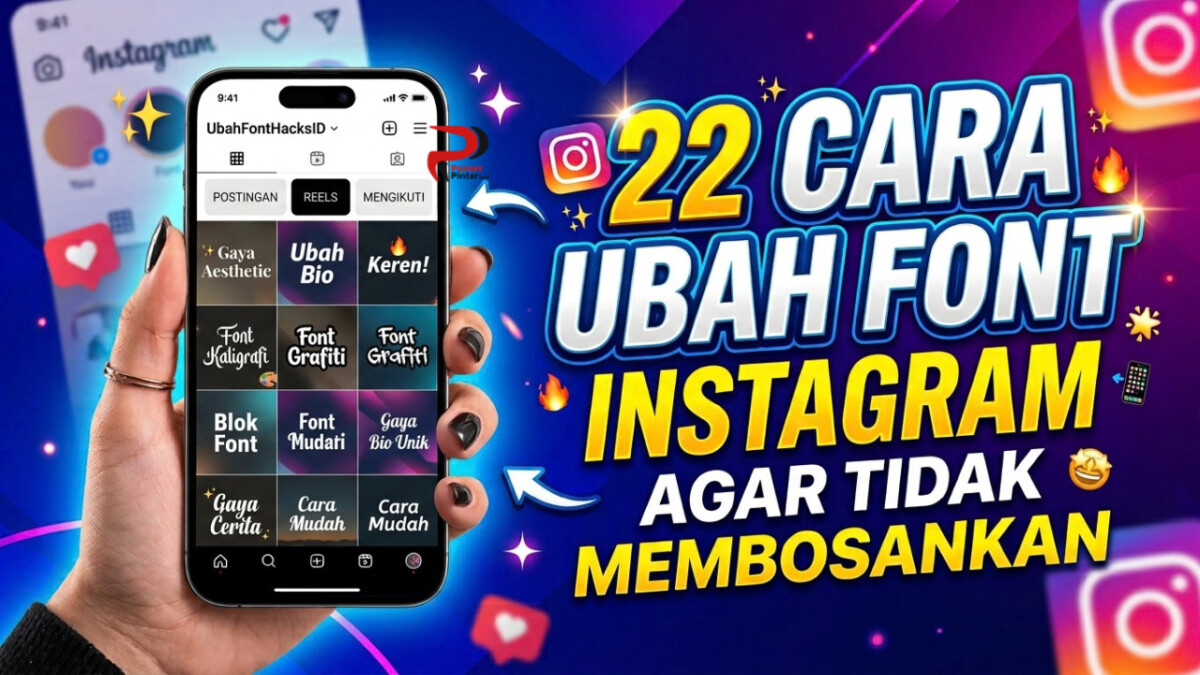
Dengan penggunaan font yang unik dan beda dari yang lain, bio Instagrammu akan tampak lebih menarik dan pastinya estetik. Untuk mengubah font Instagram menjadi lebih menarik, berikut cara-cara yang bisa kamu lakukan:
1. Generator Font Sosmed
Mengubah font sosial media, termasuk Instagram menjadi lebih unik dan estetik sangat mudah untuk dilakukan. Karena saat ini, sudah banyak generator online yang memang menyediakan layanan pengubah font ini. Bahkan untuk menggunakannya pun sangat mudah tanpa perlu login atau mendaftar akun.
Salah satu generator online yang bisa Anda manfaatkan untuk mengubah font Instagram menjadi lebih unik adalah Generator Font Semua Sosmed yang tersedia pada situs Convertmee.com. Bukan hanya Instagram saja, namun generator ini kompatibel dengan sosmed lainnya seperti WhatsApp, Facebook, TikTok, dan sebagainya.
Pada generator tersebut, Anda akan menemukan sejumlah gaya teks estetik dan unk yang bisa dipilih untuk mengubah teks standar dan digunakan di Instagram. Adapun langkah-langkah penggunaannya adalah sebagai berikut:
Apabila ingin melihat jenis teks unik dan estetik lainnya yang tidak ada di generator ini, Anda bisa mengakses generator lainnya yang juga tersedia di situs Covertmee dan mendukung penggunaan di Instagram pula. Misalnya seperti Fancy Text Generator, Generator Font Instagram, Generator Font Simbolik, dan sebagainya.
2. Cool Symbol
Situs ini juga menyediakan berbagai koleksi jenis teks unik yang dapat Anda gunakan untuk mengubah teks standar.
3. LingoJam
LingoJam pun dapat Anda kunjungi untuk menemukan berbagai jenis teks unik lainnya.
4. Meta Tags Font Generator
Anda juga dapat melihat pratinjau saat mengubah font dengan layanan ini.
5. Instafonts
Berbagai jenis font dapat Anda temukan juga pada situs ini untuk digunakan di Instagram.
6. Font Bio
Platform ini dirancang secara khusus untuk membantu pengguna Instagram merapikan bio hingga caption postingan.
7. Cool Font
Variasi teks unik bisa Anda lihat dan gunakan juga pada situs Cool Font.
8. Fancy Text Guru
beraneka ragam huruf atau teks bergaya bisa didapatkan juga setelah mengunjungi platform ini.
9. Piliapp
Generator teks unik lain yang juga bisa dioertimbangkan untuk digunakan adalah Piliapp.
10. Font Changer
Mengubah huruf standar menggunakan Font Changer juga dapat dilakukan dengan mudah.
11. Fonts Online
Alternatif lain yang bisa Anda gunakan untuk menemukan font unik adalah Fonts Online.
12. Logwork Instagram Fonts
Jika ingin mengubah tulisan menjadi glitch, platform ini cocok untuk dicoba.
13. Fonts Studio
Beragam jensi tulisan unik bisa didapatkan melalui situs satu ini juga.
14. IFonts
Alat untuk mempercantik profil Instagram dengan tulisan unik juga dapat ditemukan pada situs IFonts.
15. Text Trick
Teks bergaya artistik bisa Anda bentuk di situs Text Trick.
16. Instagram Fonts FR
Merupakan salah satu situs web dengan bahasa prancis yang dapat membantu untuk urusan font estetik.
17. Bold Texts
Lebih berfokus pada teks tebal dan miring. Jadi jika Anda membutuhkannya, Anda juga dapat mengakses Bold Texts.
18. Aesthetic Font
gay huruf dan lembut bisa Anda gunakan pada Aesthetic Font.
19. Fancy Text Tool
Memodifikasi huruf standar bisa dilakukan juga dengan menggunakan Fancy Text Tool.
20. Unicode Text Converter
Huruf biasa bisa Anda ubah juga menjadi kode karakter khusus unicode unik dengan menggunakan Unicode Text Converter.
21. IGFonts
Cara pertama untuk dapat mengubah font Instagram adalah melalui IGFonts. Adapun langkah-langkah penggunaannya adalah sebagai berikut:
- Pertama, kunjungi situs igfonts.io terlebih dahulu
- Kemudian, silahkan Anda ketik teks yang akan Anda cantumkan pada profil IG di kolom “Add text here”
- Berikutnya, Anda dapat scroll ke bawah
- Lalu Anda dapat menemukan pilihan font yang muncul dalam beberapa saat. Terdapat beberapa pilihan font yang tersedia dan bisa Anda gunakan secara gratis
- Sedangkan pada bagian bawah, Anda dapat melihat hasil teks yang telah Anda ketik sebelumnya dengan pilihan font yang beragam
- Cara mengubah font di bio Instagram selanjutnya adalah scroll ke bawah untuk dapat melihat opsi lainnya.
- Setelah Anda menemukan font yang telah Anda inginkan, maka copy teks dengan jenis font tersebut.
- Jika seluruh teks berhasil Anda salin, maka kembali ke aplikasi IG supaya Anda dapat mengubah font pada bio
- Lalu silahkan buka pengaturan akun pada menu “edit profile”
- Paste teks pada kolom bio Instagram, lalu save pengaturan dengan klik “Done”. Maka font bio IG telah berhasil Anda ubah.
22. Aplikasi Cool Fonts
Cara kedua untuk mengubah font Instagram adalah melalui aplikasi Cool Fonts. Adapun cara menggunakannya ialah sebagai berikut :
- Silahkan install aplikasi Cool Fonts by Pixster Studio di perangkat Anda.
- Berikutnya buka aplikasi tersebut.
- Pada halaman awal, Anda dapat tekan tombol GET STARTED.